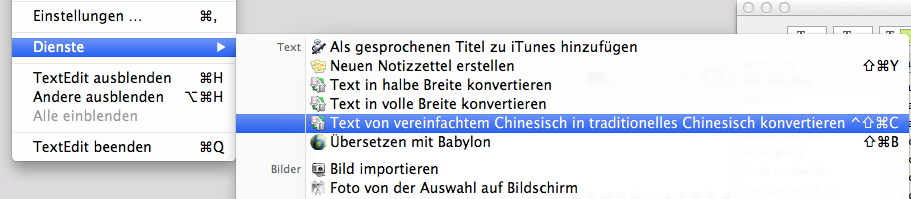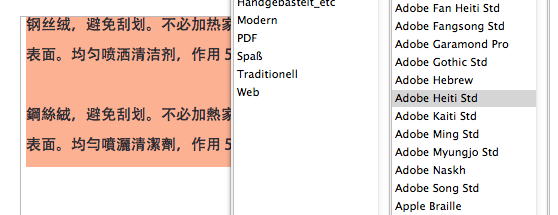
[InDesign] Wie sortiert ID die CJK-Sprachen im Fenster?
Jenes Bild ergibt sich, wenn die eine oder andere CJK-Sprachen aktiviert ist. Nach was unterteilt ID denn hier?
Japanisch
Chinesich Lang (HK u. Taiwan)
Chinesisch Kurz (VR Ch)
Koreanisch
Arabisch
Ivrit
Devanagari ("Indisch")
Was würdest du für einen Produktnamen empfehlen, der in China und eventuell in anderen chinesischsprachigen Gebieten vertrieben wird – lang? Oder ist die verkürzte Schrift mittlerweile überall verbreitet?
In Hongkong kann man zwar die meisten Kurzzeichen verstehen, liest es aber ungern, in Taiwan hingegen ist es schon fast ein Politikum – obwohl zahlreiche der Kurz-Varianten viele hundert Jahre alt sind. Dafür sind die Langzeichen in der VR nicht mehr verpönt, im Gegenteil: Sie haben sogar ein wenig mehr "Sozialprestige". Darum würde ich Langzeichen verwenden. Da aber nur eine bestimmte Anzahl Zeichen "verkürzt" sind (nämlich nur die arg komplizierten), kann es sogar sein, dass der Name "sowohl als auch" ist. Wenn du magst, schick mir den Namen mal per PN, dann kann ich dir eventuell ein wenig besser raten.
烤箱喷雾式清洁凝胶
Das soll "Backofenreiniger Gel Spray" heißen.
PS: Eine "Marke" kann auch kalligrafisch gelöst sein, d.h. es wäre dann ohnehin wurscht, ob lang oder kurz.
Der Name ist nur die Übersetzung einer Produktbezeichnung und kein eigener Produktname, da hab ich mich vorhin falsch ausgedrückt.
Dass das eine Übersetzung ist, habe ich mir schon gedacht, das ist ein bisschen sehr wörtlich. Ich recherchier mal, ob die Produktbezeichnung so überhaupt geläufig ist, mir kommt sie zu holprig vor.
(Vor allem das "Gel" ist mehr "Gelatine" als so Seifenzeugs).
Die Übersetzung kam vom Hersteller, drum würde ich die mal als so gewünscht stehen lassen. Auch wenn das von mir aus "Backofenreiniger Sprühgelatine" heißt ;-)
Also, Gel passt, K2R heißt auch so: 烤箱清潔凝膠 (das sind jetzt übrigens Langzeichen; 胶=膠, 洁=潔). Und das Spray (喷雾) passt auch, wäre in Langzeichen 噴霧.
Falls dir das einfache Umstellen vom Font nicht weiterhilft, und du trotz Langzeichenfont die Kurzzeichen siehst, müsstest du über "Dienste" die Kodierung ändern.
Wobei ich eine Produktbezeichnung nicht unbedingt in Langzeichen machen würde, wenn ich's mir recht überlege ... wenn es erstmal hauptsächlich für die VR ist, dann lieber Kurzzeichen. Wenn's dann später mal nach Taiwan exportiert wird, dann Langzeichen für dort.
Das hier ist der gleiche Text in der gleichen Schrift, einmal kurz, einmal lang – Einstellung über "Dienste".